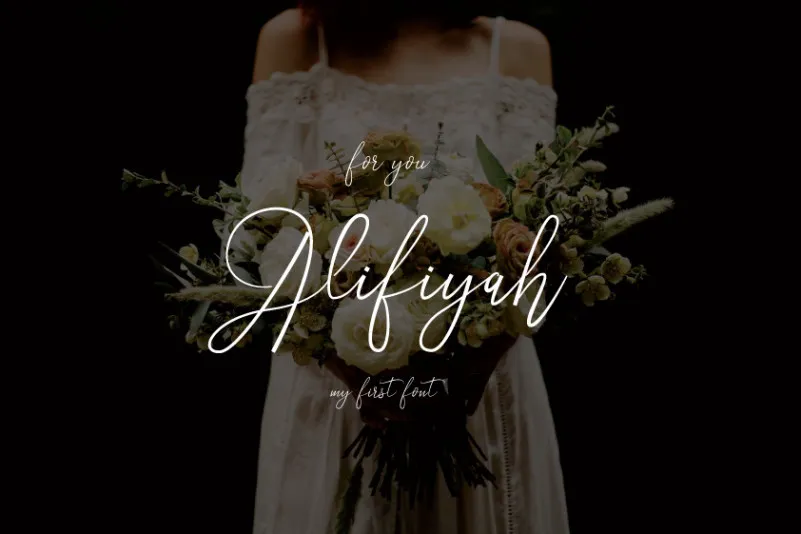
Alifiyah Handwritten Font – Download Grátis
A fonte Alifiyah Handwritten é inspirada na beleza feminina com suas nuances suaves. Inspirada nos traços delicados e delicados das escritas à mão, esta fonte transmite sofisticação e elegância com seus contornos perfeitamente definidos. Seu design exalará estilo em qualquer projeto que você desenhe, destacando sua composição de forma impressionante e inovadora. Ideal para aplicações que valorizam uma sensação única e emocionalmente reivindicativa, a Alifiyah Handwritten é perfeita para criar um toque final que remete à natureza da elegância humana.